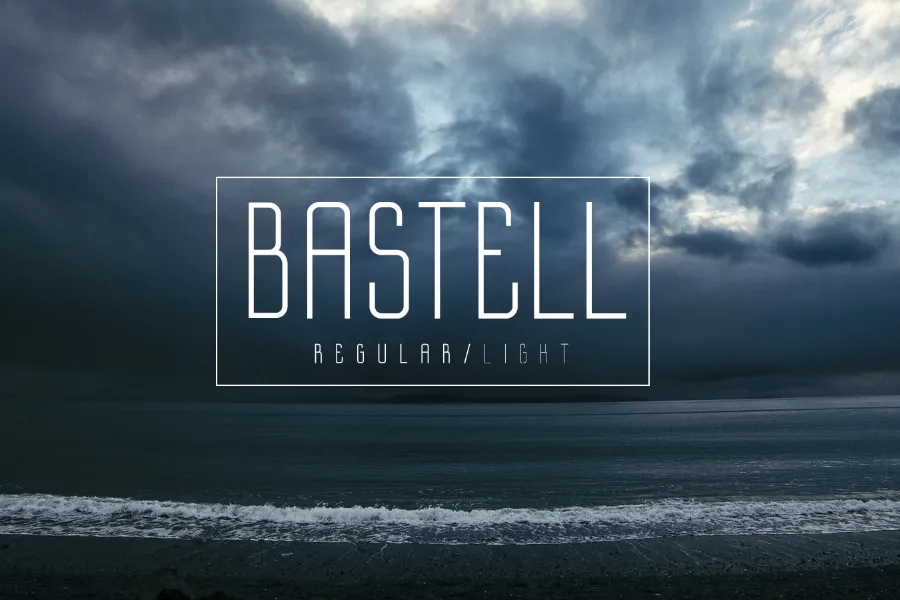
Bastell Typeface
Bastell é uma fonte sans-serif que surgiu do trabalho meticuloso de Hamilton. Esta opção elegante e versátil é perfeitamente adequada para diversas aplicações, desde logotipos até arte de capa de álbum, passando por roupas e gráficos criativos em geral. A Bastell oferece tanto um Regular quanto uma variante Light que se adapta a diversos estilos e ambientes visuais. Seu formato redondo e semi-condensado cria um equilíbrio arquitetônico que, ao mesmo tempo, permite maior expressividade do texto. É perfeito para quem busca um toque de sofisticação sem abandonar os benefícios de uma fonte sans-serif. Bastell é gratuita tanto para uso pessoal quanto para projetos comerciais, permitindo que você explore e utilize esta bela fonte em suas criações de design gráfico.